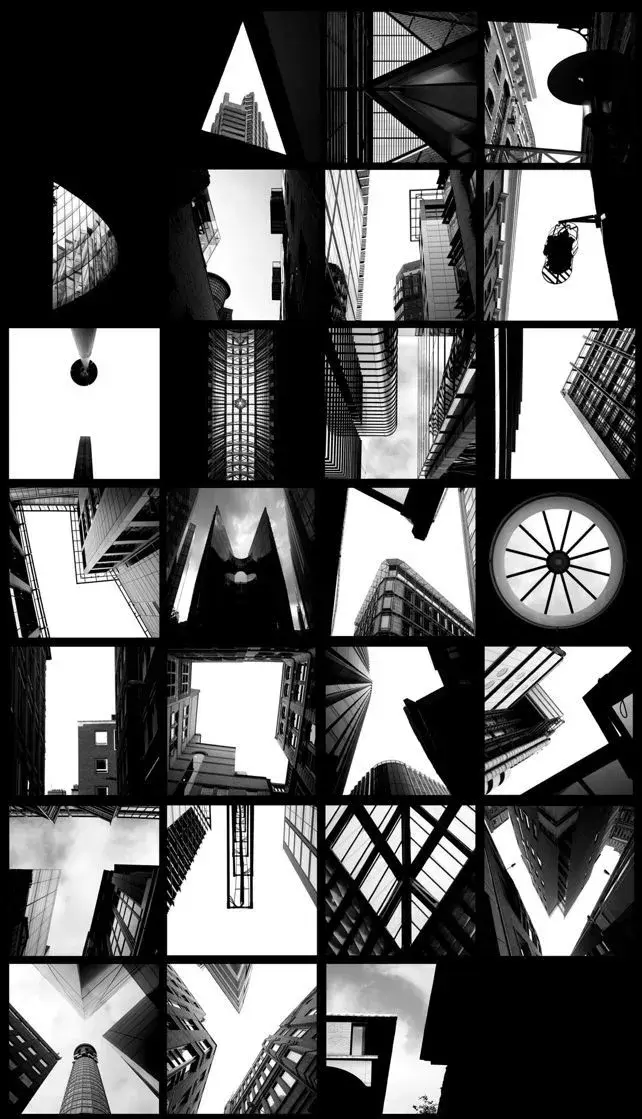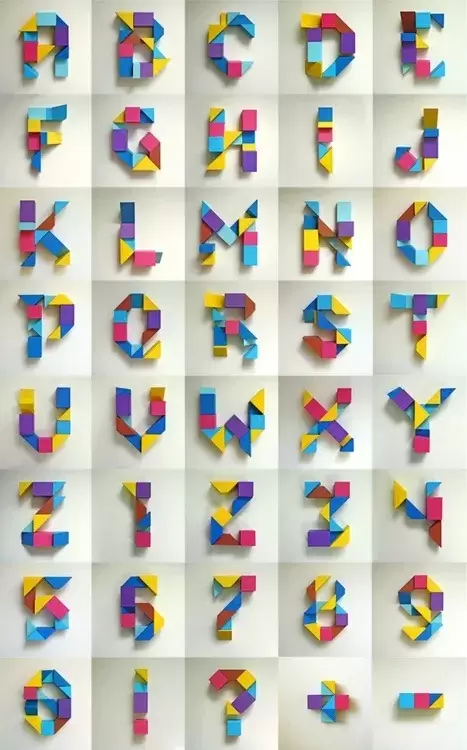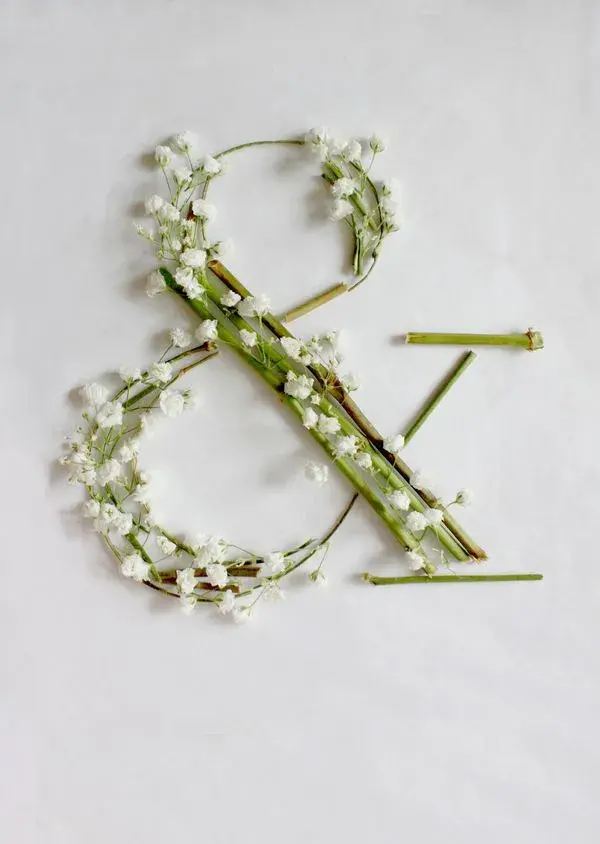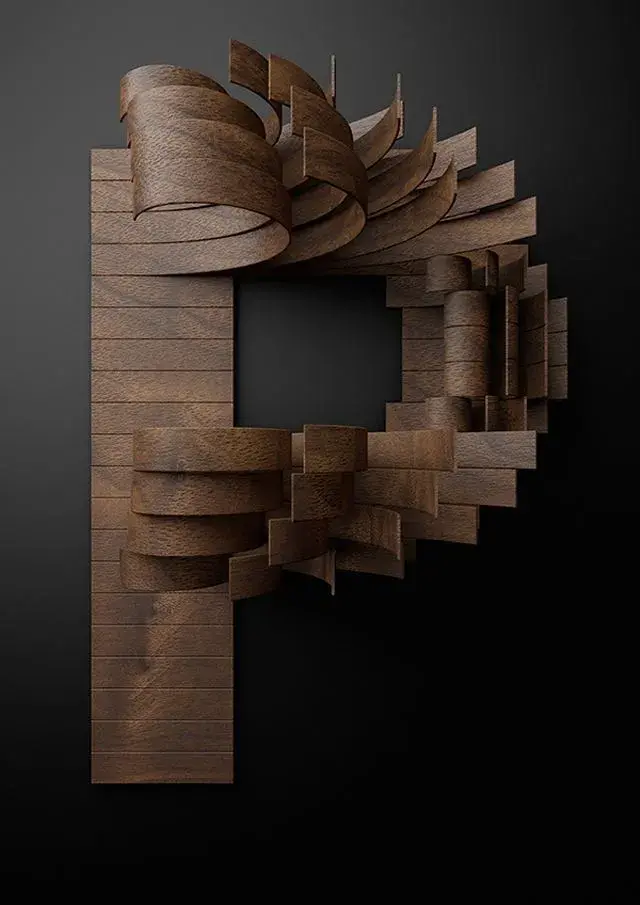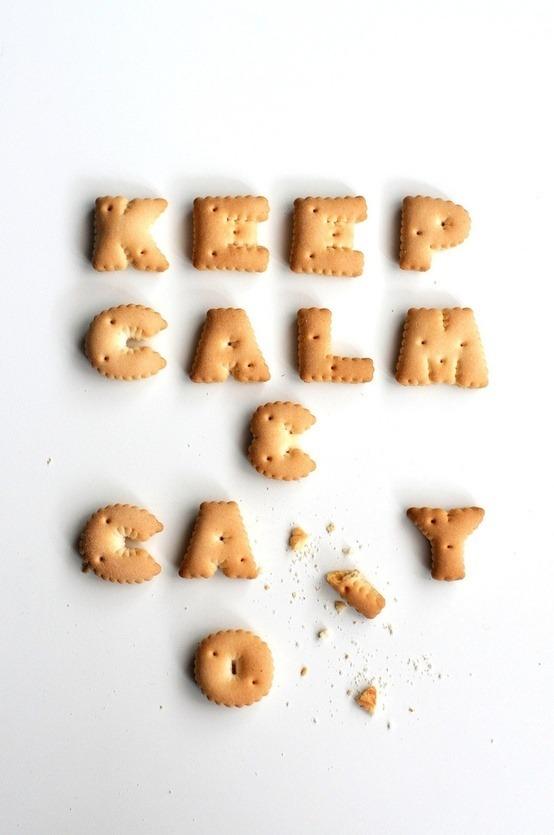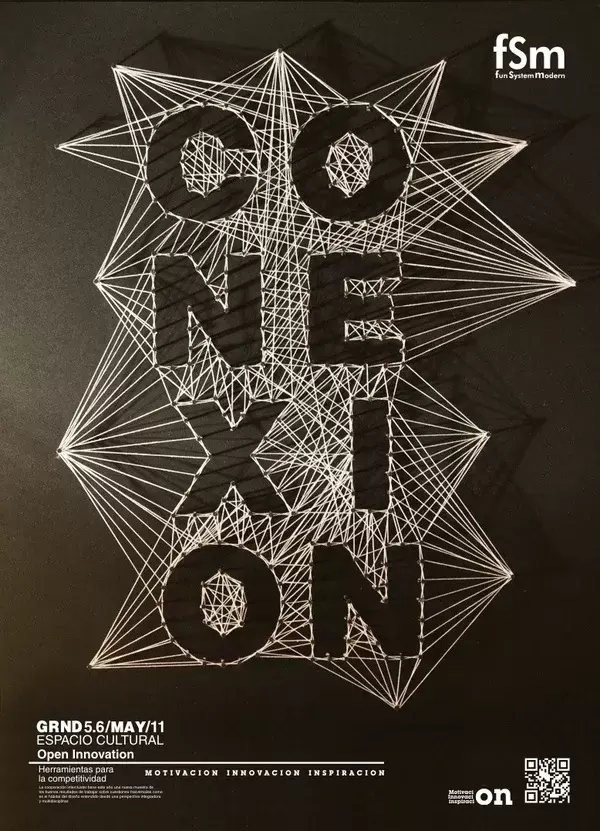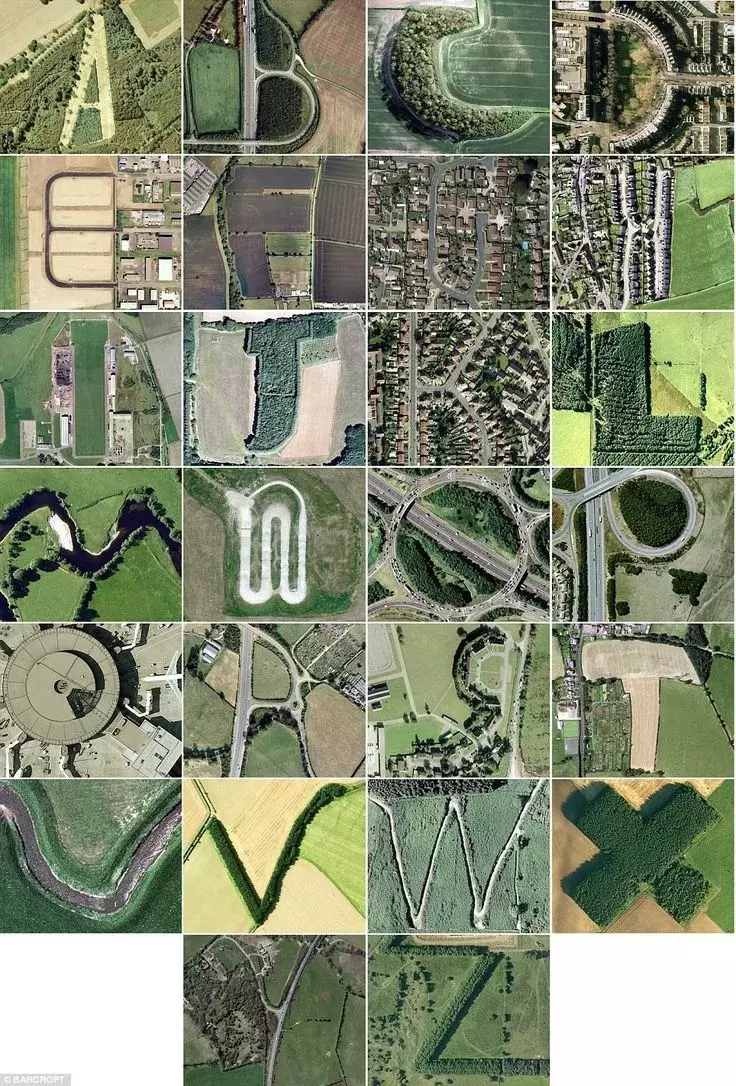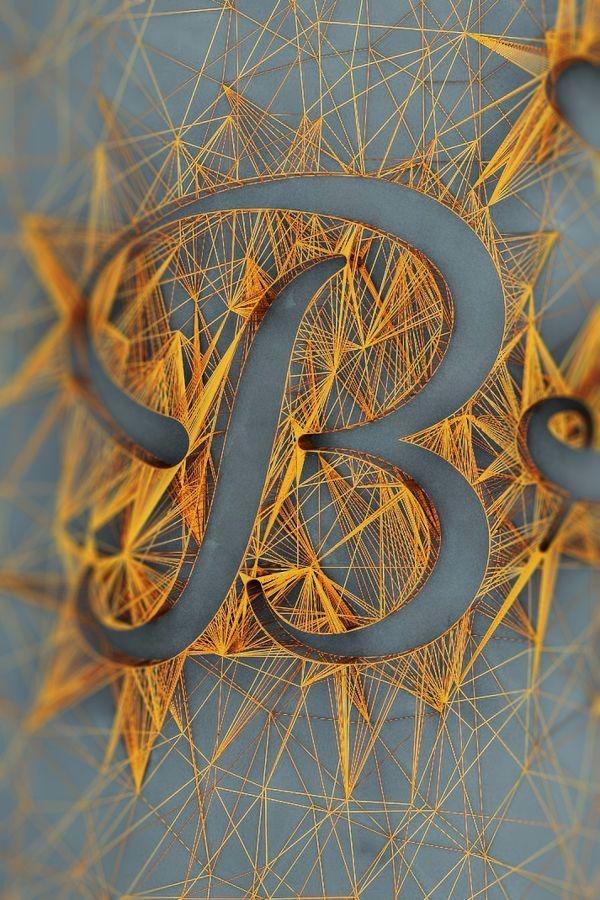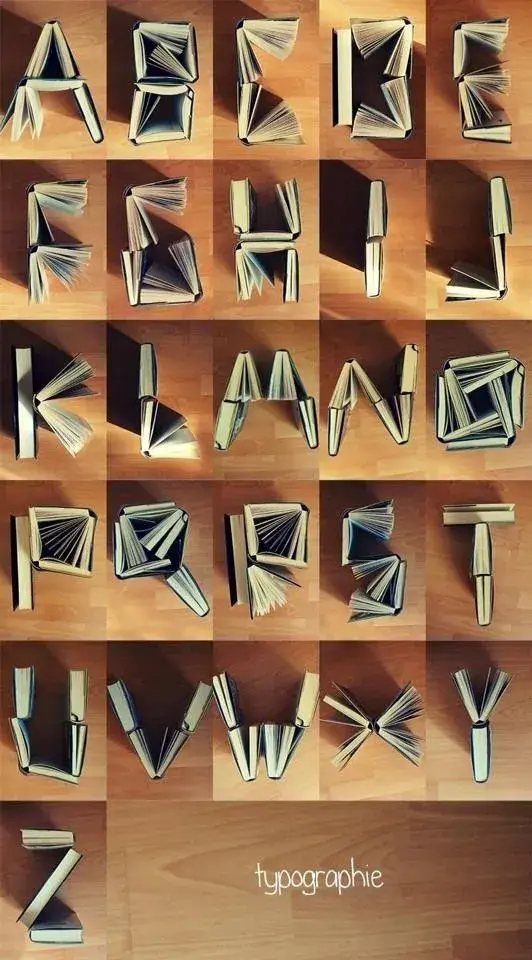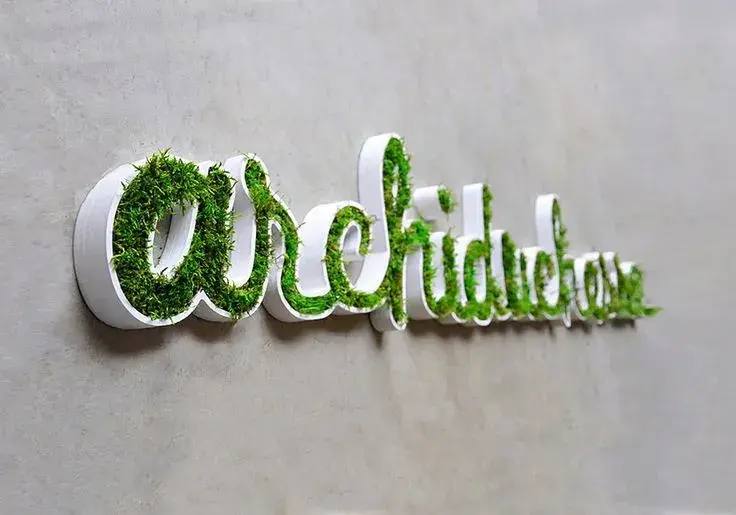
16 typographies créatives réalisées avec des objets
Découvrez 16 typographies originales et créatives réalisées grâce à des objets !
Découvrez une sélection de créations réalisées à l'aide d'objets pour amener un côté original et surprenant à la typographie. Certaines créations utilisent des objets afin de connoter la lettre, tandis que d'autres l'utilisent simplement pour la dessiner.
Une bonne dose d'inspiration et d'originalité à voir dans la suite de l'article.
The Quick Brown Fox Dan Hoopert
Alphabet Leaves – Georgia Jeffery
Expressive Typeface – Baby's Breath par Keziah Chong
Nike Typography with Wooden Slats
Typographie Books par Noémie Lacarelle
Blocs letters
Pebbles inspire me
ALPHATECTURE by Peter Defty
Paper by Alistair Hall
The Google Earth alphabet found in Britain's hedgerows
Typography par Sabeena Karnik
Ignite de Farah Tamachi
Typographie végétale
Open Innovation par Koke Romero
Wire & Mesh : Typographie par Dan Hoopert
Old Design Meme: Keep Calm & Carry On